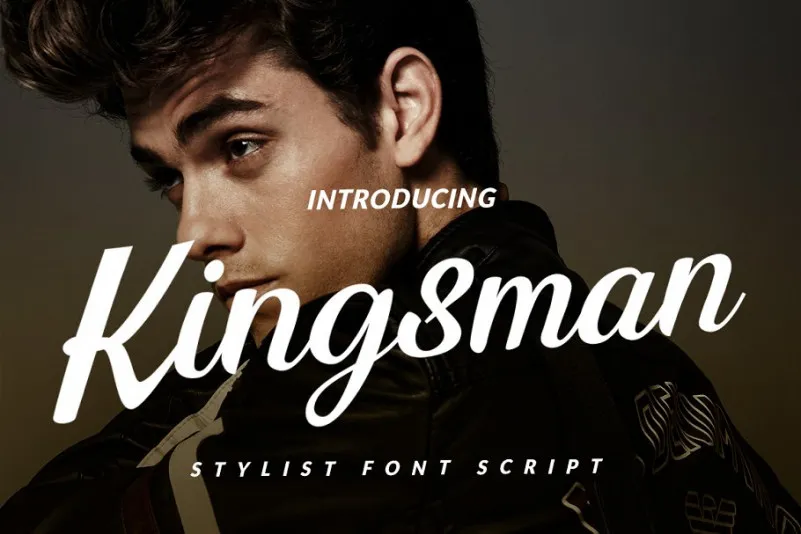
Kingsman Stylist Script Font
Aqui está uma breve descrição em português para a página de download da font ‘Kingsman Stylist Script Font’: Se você procura uma nova opção de tipo script que seja tanto funcional quanto estilosa, Kingsman Script Font é uma ótima escolha. Este novo elemento tipográfico vem com um estilo dual e apresenta alternativas de caractere e ligaturas para oferecer flexibilidade em seu uso. Seu design elegante e legível torna-o perfeito para criar logomarcas de produtos, cartões de casamento, marcas de roupas e até mesmo para arquitetura vintage. O designer M.0Type tem trabalhado na Kingsman Script Font com a intenção de mantê-la minimalista mas poderosa, tornando-a uma opção ideal para diversos estilos gráficos. Para aqueles que valorizam um tipo que pode ser transformado em cada palavra – seja em logomarca ou qualquer outro elemento visual – esta fonte é certamente o item que procurava. Seja você um designer de produto, um casal criando cartões de noivado, uma marca de roupas querendo estabelecer sua identidade visual ou até mesmo aqueles amantes da arquitetura vintage procurando por uma fonte única – Kingsman Script Font está aqui para ajudá-los a criar elementos visuais inovadores e memoráveis.